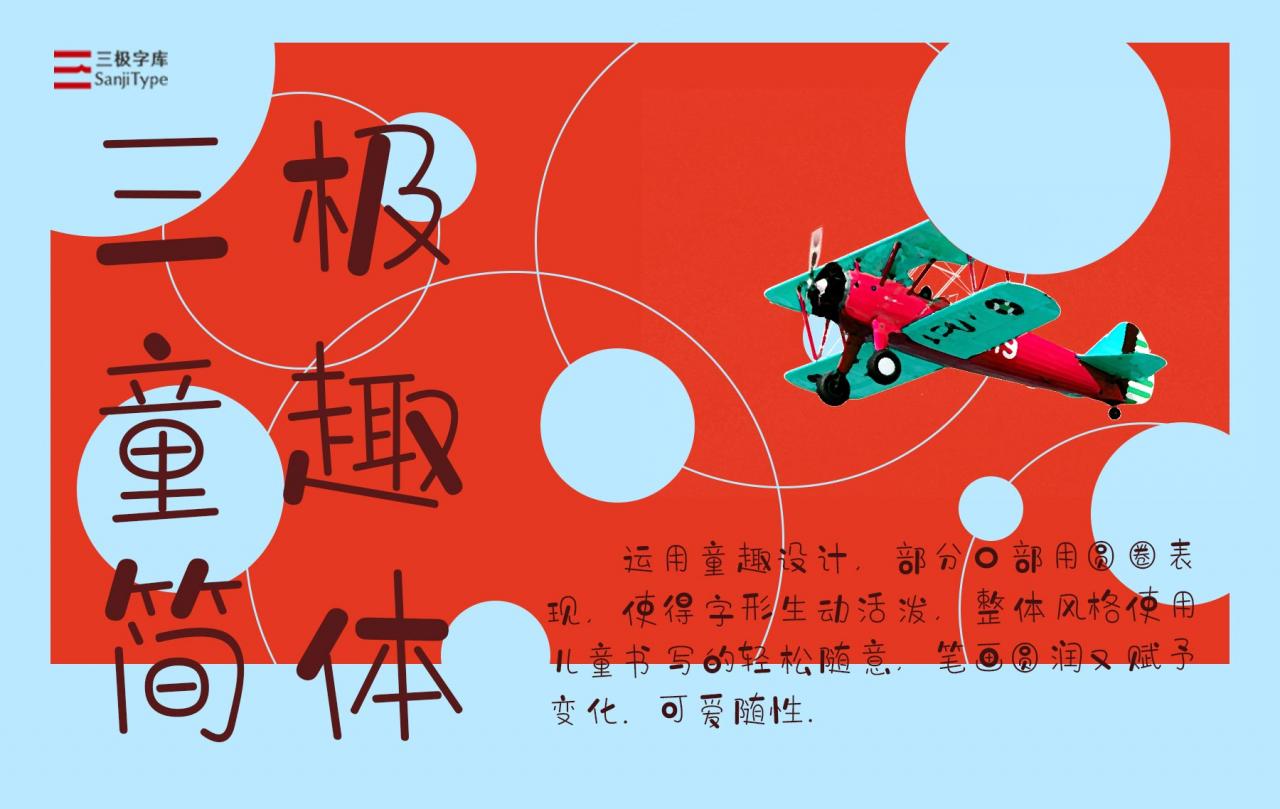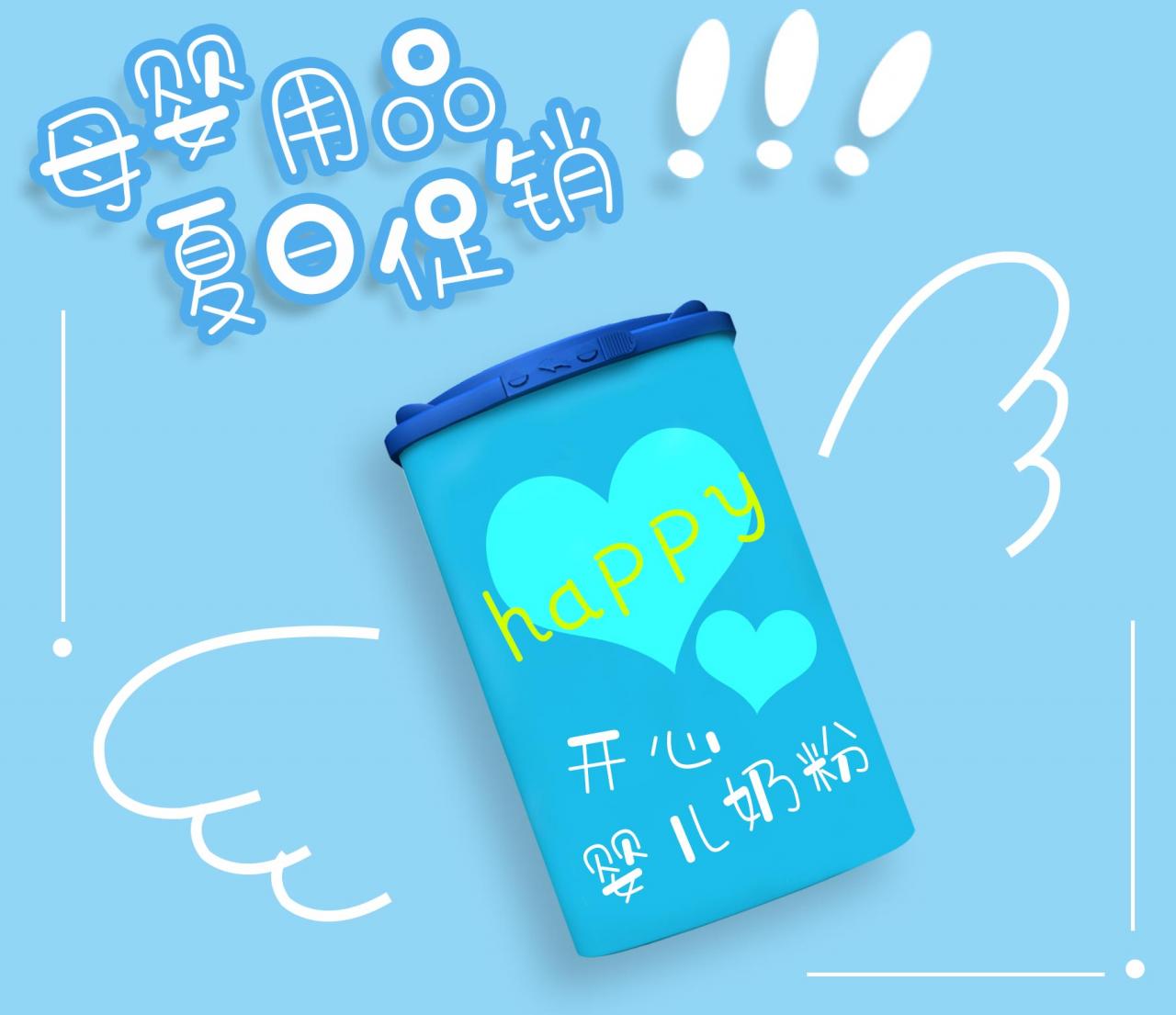
三极童趣简体
字体名称:三极童趣简体
设计师:李文浩
三极童趣简体运用童趣设计,部分口部用圆圈表现,使得字形生动活泼,整体风格使用儿童书写的轻松随意,笔画圆润又赋予变化。可爱随性。适用于少儿类读物、书刊、品牌广告、母婴用品包装设计以及社交网络个性化用字。
适用媒介:杂志、书籍、广告、标志、宣传册、包装、影视、动漫、屏幕显示、交互设计。